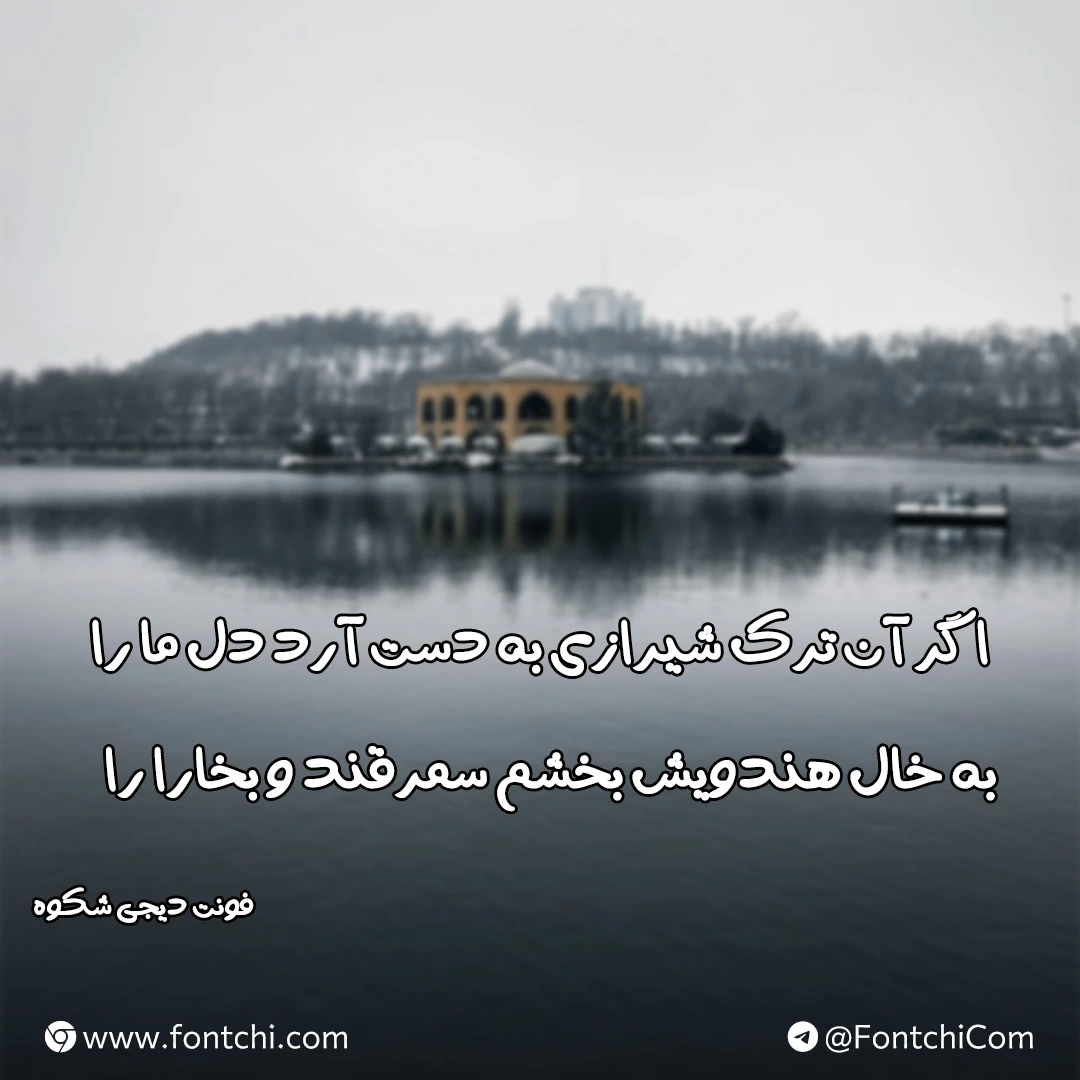
فونت دیجی شکوه (Digi Shokoh)
فونت دیجی شکوه یا شکوه (به انگلیسی: Digi Shokoh) نسخه‌ای فارسی شده و برگردان از یک فونت عربی دست نویس است که می‌توانید از آن برای ساخت تصاویر عکس نوشته با متون کوتاه استفاده کنید. با توجه به اینکه این فونت نسخه‌ای دستکاری شده از فونت عربی است برخی گلیف‌ها مانند اعداد را ندارد.
اما به طور کی اگر به دنبال فونتی دست‌نویس برای استفاده در تصاویر عکس‌نوشته، دل نوشته، عناوین کوتاه، استوری‌های اینستاگرام یا تلگرام هستید می‌توانید از این فونت استفاده کنید. نسخه برگردان این قلم عربی به فارسی توسط مهدی برقگیر انجام گرفته است.
طراحی فونت شکوه بر اساس سبک فونت‌های ماژیکی صورت گرفته که پیش از این در فونت آوینی یا فونت جوان چنین سبکی را دیده‌ایم. قلم‌هایی با این سبک دارای کشیدگی‌های خاص خود هستند که در سبک نقطه‌گذاری نیز عموما از نقطه گرد استفاده می‌شود که به صمیمی‌تر کردن فونت کمک می‌کند.
فونت دیجی شکوه که بر پایه یک فونت عربی طراحی شده، از زبان‌های فارسی و انگلیسی نیز پشتیبانی می‌کند. برای زبان فارسی گلیف‌های «گ، چ، پ، ژ» به این فونت افزوده شده و حروفی مانند «و، ه، ی» عربی که دارای دو نقطه یا همزه هستند نیز مخصوص فارسی پیاده‌سازی شده است. اما شاید تنها کاستی این فونت در بخش اعداد باشد که فاقد گلیف برای زبان فارسی هستند.
در حالی که برای زبان عربی و انگلیسی توسط طراح اصلی فونت این گلیف‌ها به صورت استاندارد طراحی شده و تنها در حالت زبان فارسی نمی‌تواند از اعداد فارسی استفاده کرد که در این حالت از فونت پیش‌فرض سیستم عامل استفاده خواهد شد.
از دیگر کاربردهایی که این فونت دارد می‌توان به موارد زیر اشاره کرد:
• طراحی استوری و پست‌های عاشقانه در شبکه‌های اجتماعی.
• ساخت جملات تاکیدی یا شعارهای تبلیغاتی.
• استفاده در طراحی جلد کتاب حوزه کودک و نوجوان.
• استفاده در کارهای خلاقانه هنری مانند مجلات.
• ساخت لوگو تایپ برای محصولات مرتبط با کودک و نوجوان.
• استفاده بر روی بسته‌بندی محصولات مرتبط با کودکان.